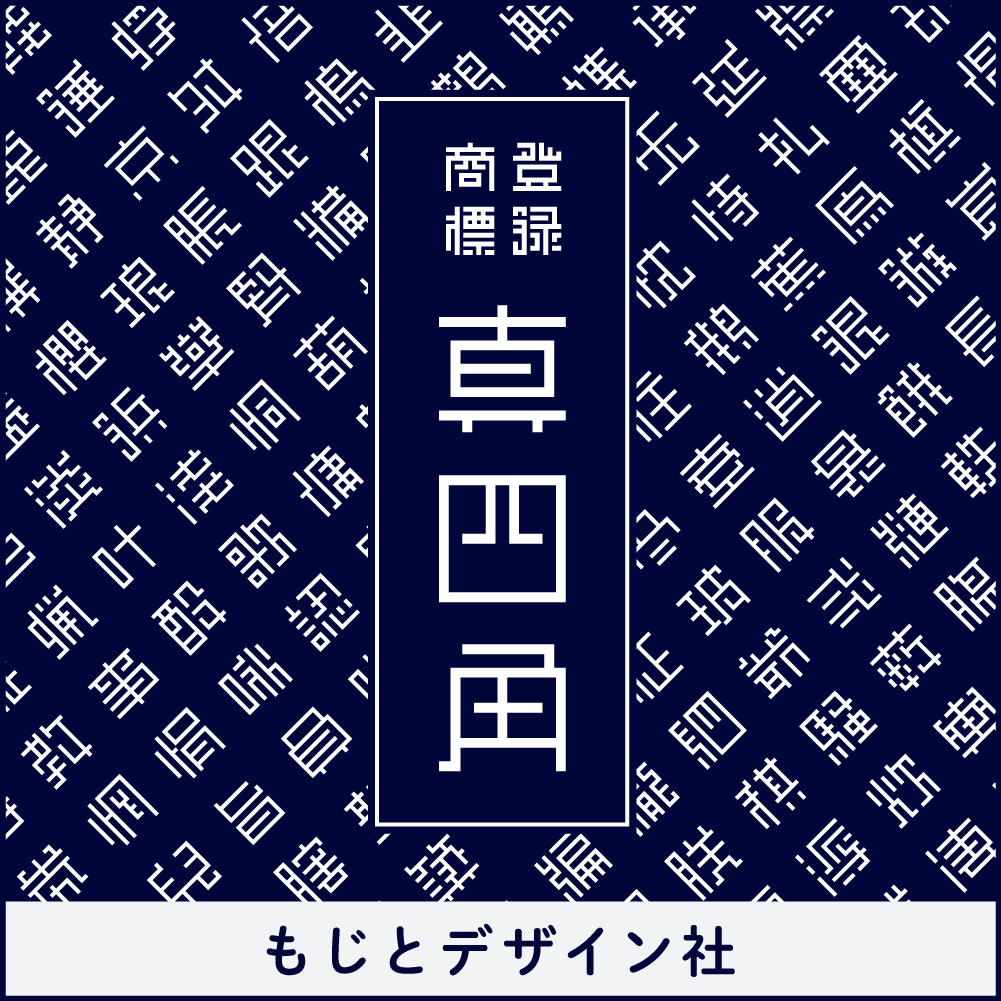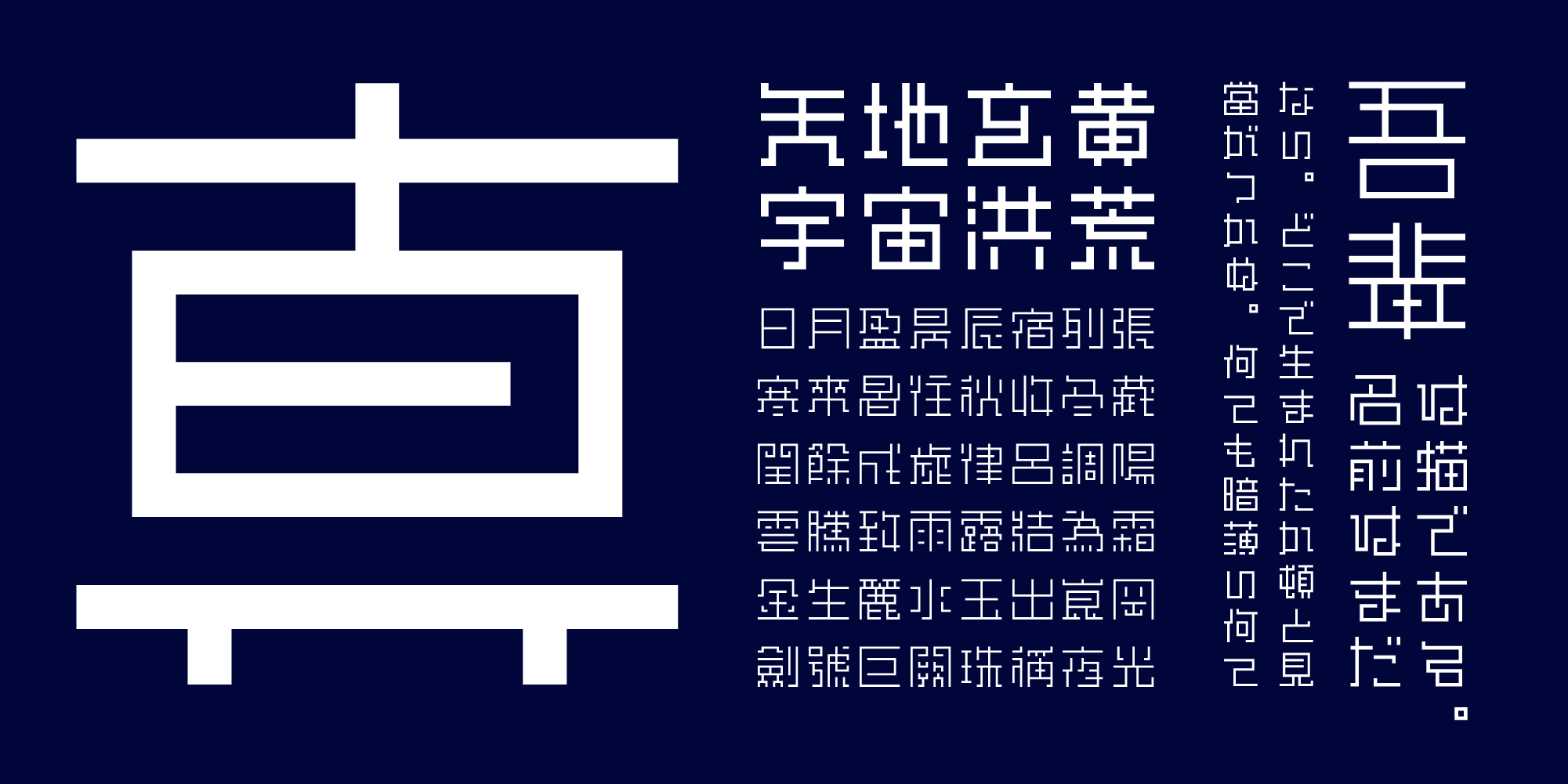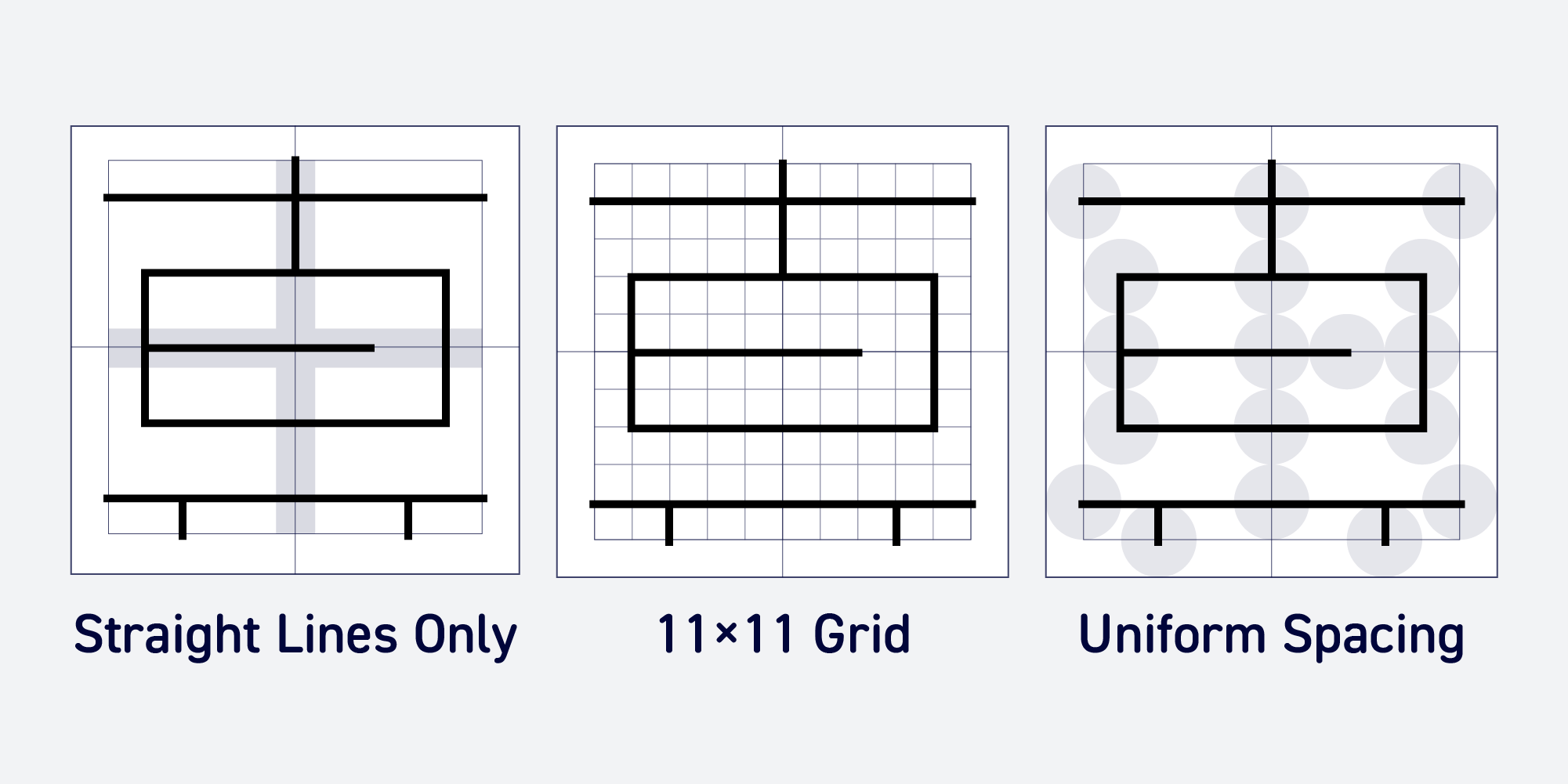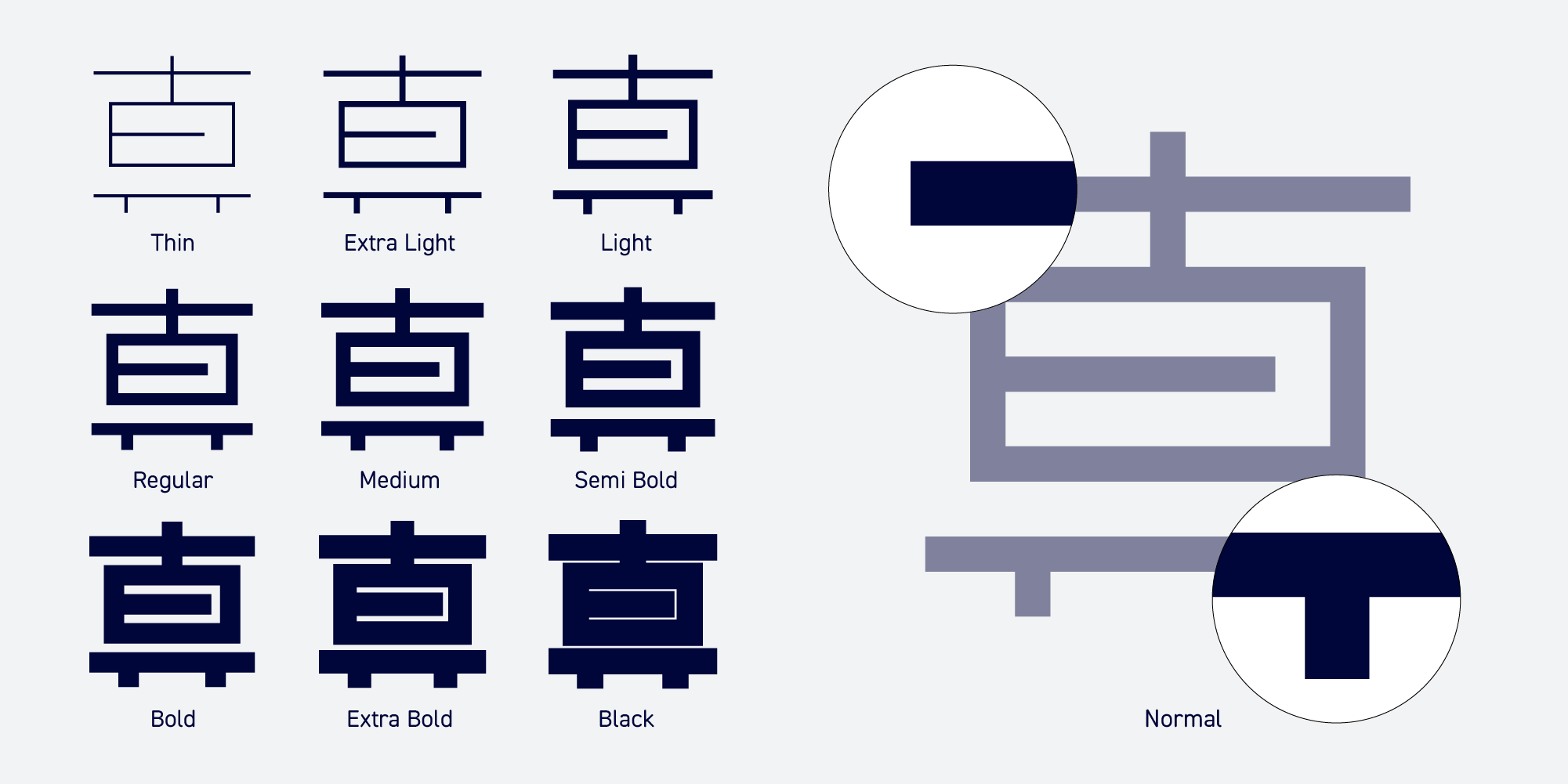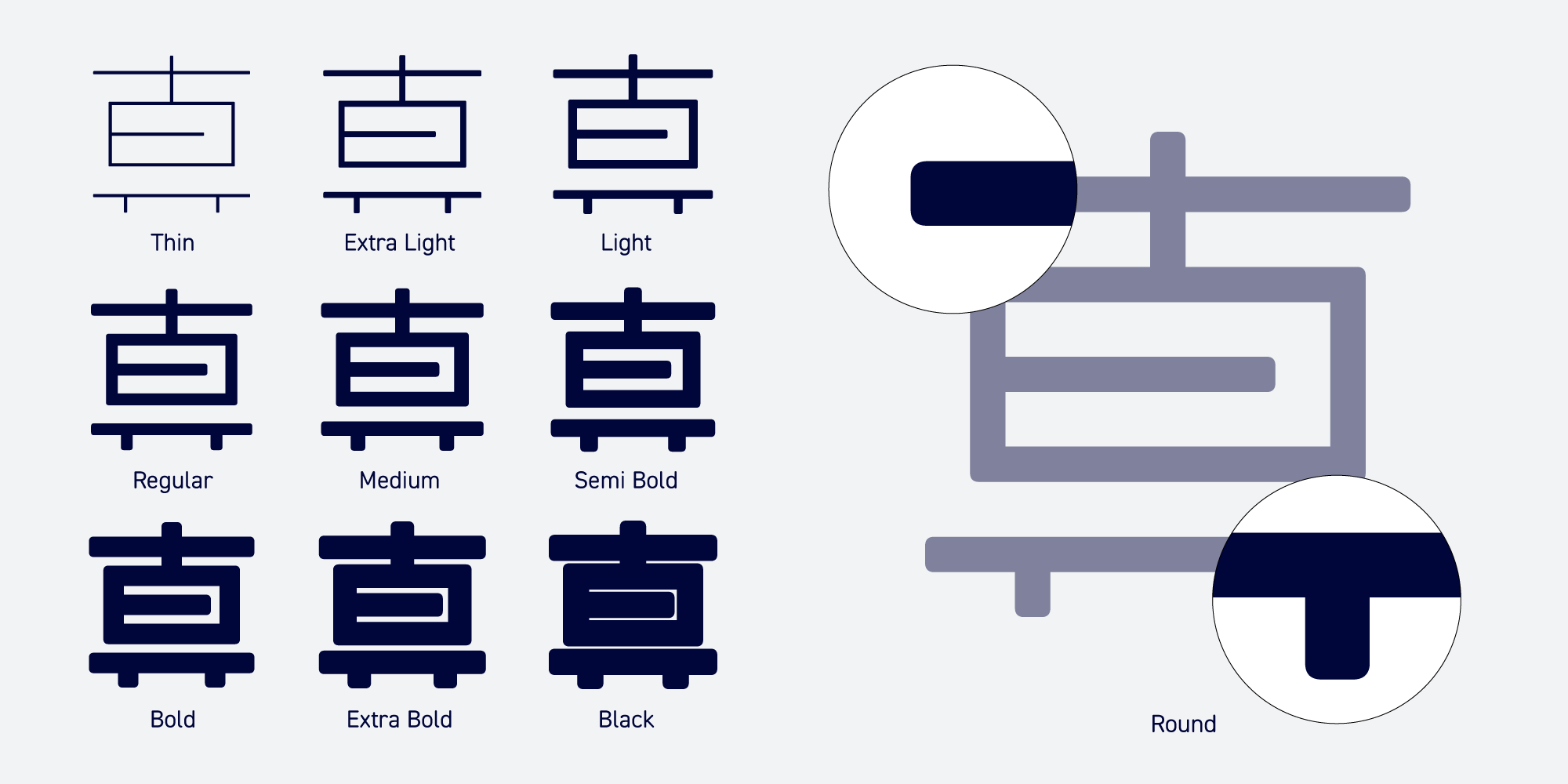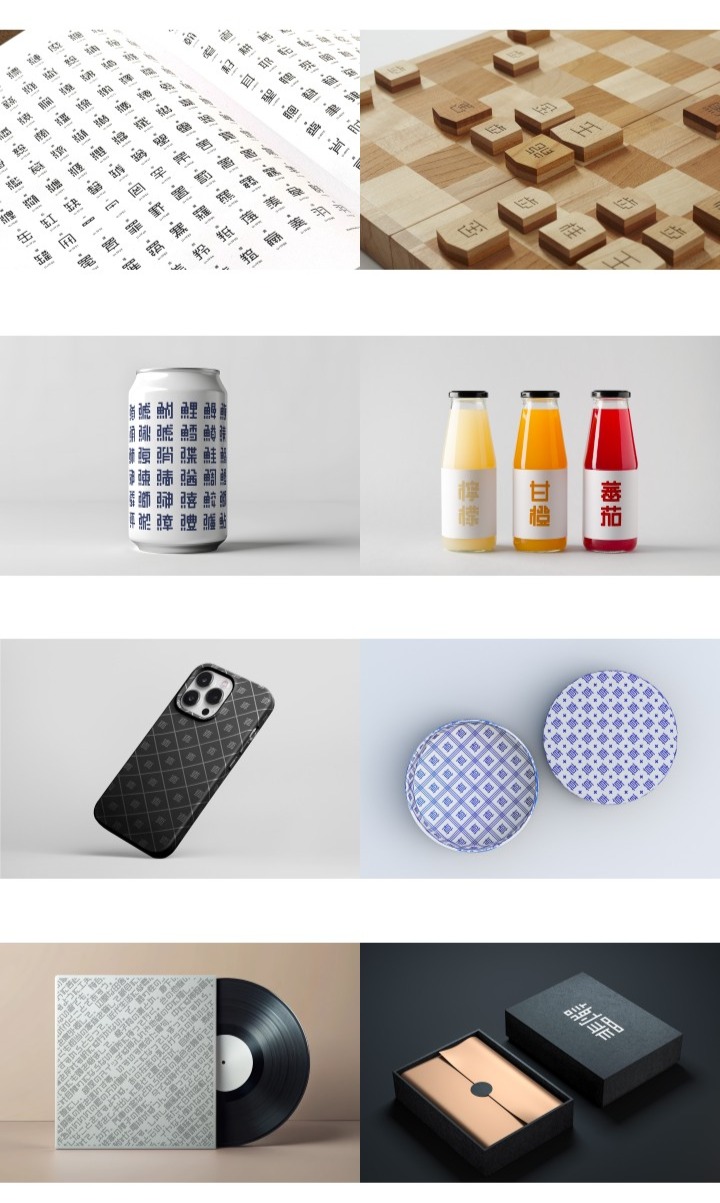
【もじとデザイン社(moji.design)】のご紹介 もじとデザイン社は、独創性あふれる真四角書体を展開するファウンダリです。真四角書体は江戸文字「角字」にインスパイアされ、正方形の中を水平・垂直の直線だけで構成した幾何学的なスタイルを特徴としています。伝統の造形を受け継ぎつつ、現代の生活空間に自然に溶け込む、シンプルで親しみやすいデザインの書体です。 |
■真四角書体
真四角書体は、江戸時代の装飾文字「角字」にインスパイアされ設計された書体です。角字が持つ直線的で幾何学的な造形を現代的に再構成し、シンプルでありながら力強い印象を生み出します。最小限の線で漢字の特徴をとらえ、簡潔さと個性を両立させることを目指しています。
漢字の特徴を最小限の線で表現することで、簡潔さと個性を両立。ウェイトは極細(Thin)から極太(Black)までの9種類を揃え、繊細な文字組から大胆な見出しまで幅広く活用できます。また、今回はNormalとRoundの2種類をご用意致しました。
Normal Type
Round Type
「暮らしの中に文字を取り入れる」という江戸の美意識を背景に、サイン、パッケージ、Web、インテリアなど、多様な場面で空間やプロダクトに存在感を与えます。